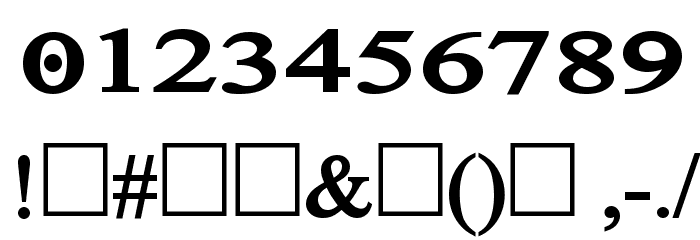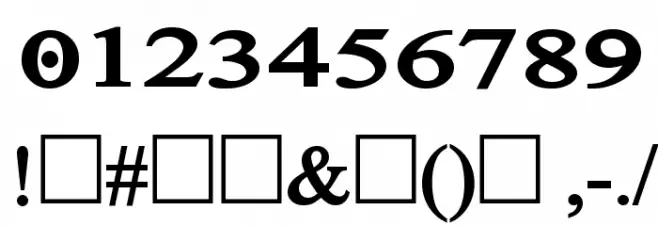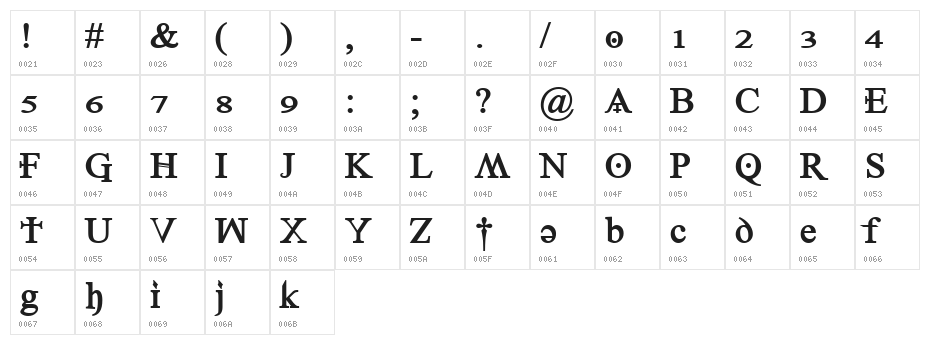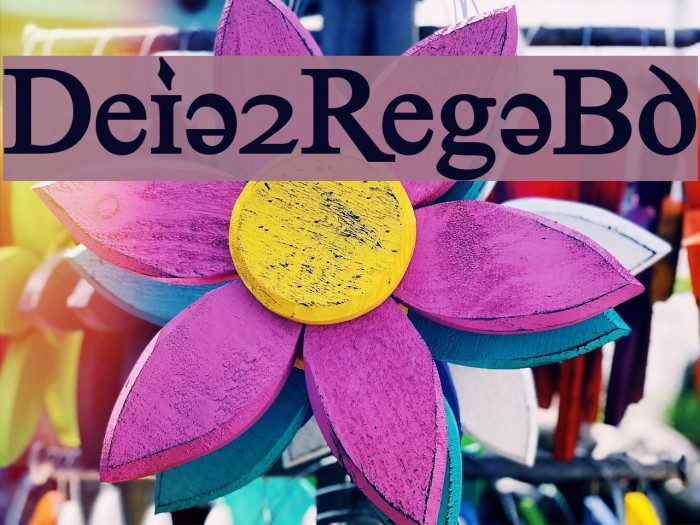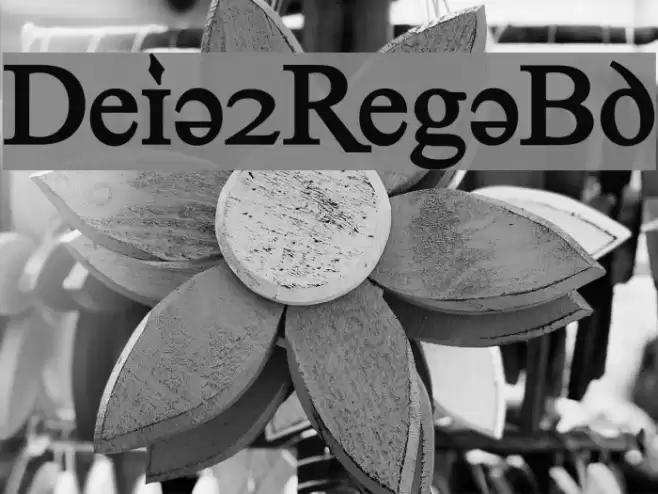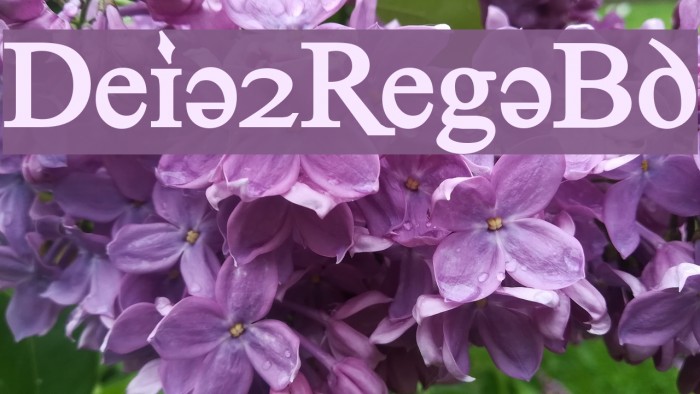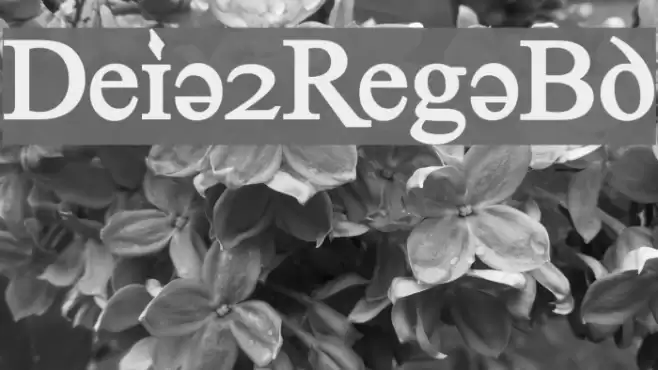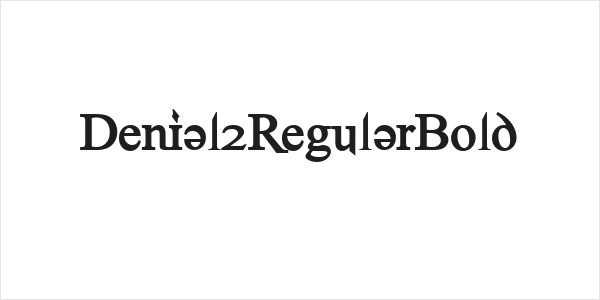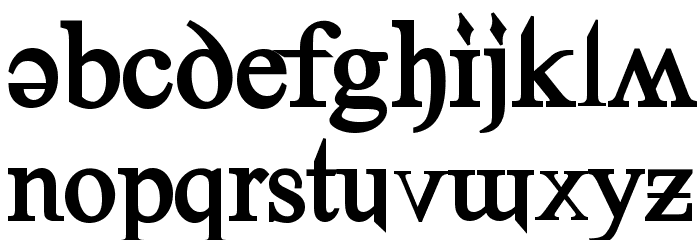
Denial2RegularBold Font
| Estilo general | Classic |
| Caso de uso | Headlines, Logos, Branding |
| Proyectos propuestos | Ideal for projects requiring a traditional and authoritative look, such as book covers, formal invitations, and branding materials. |